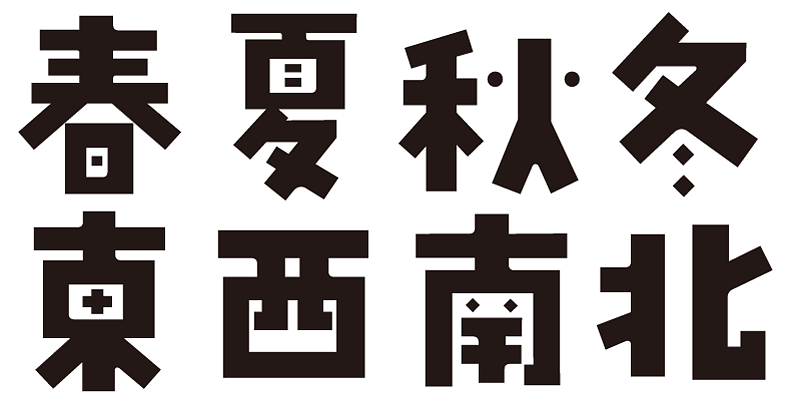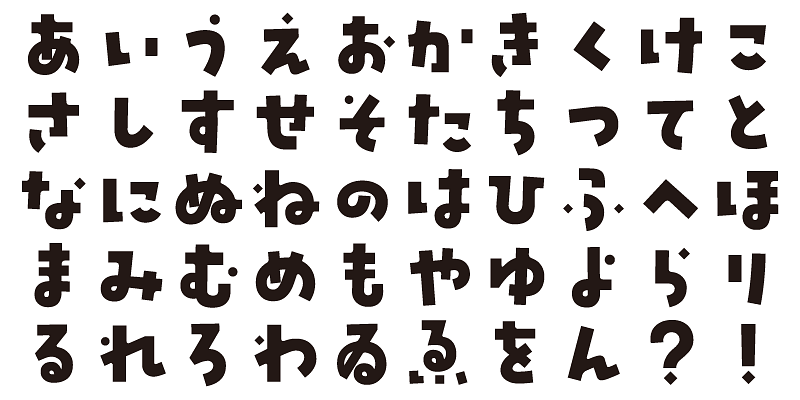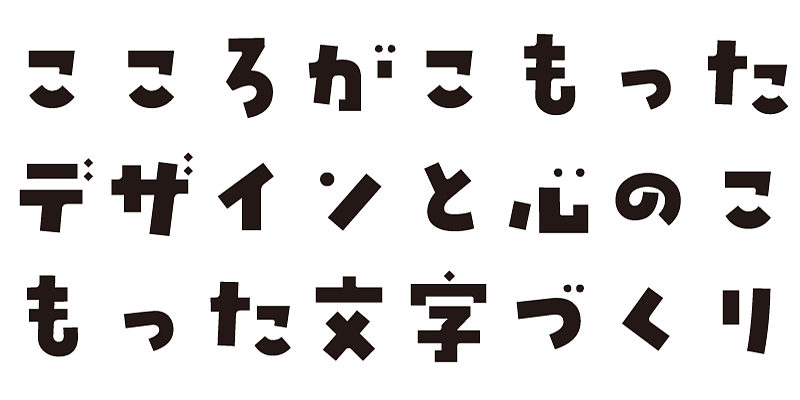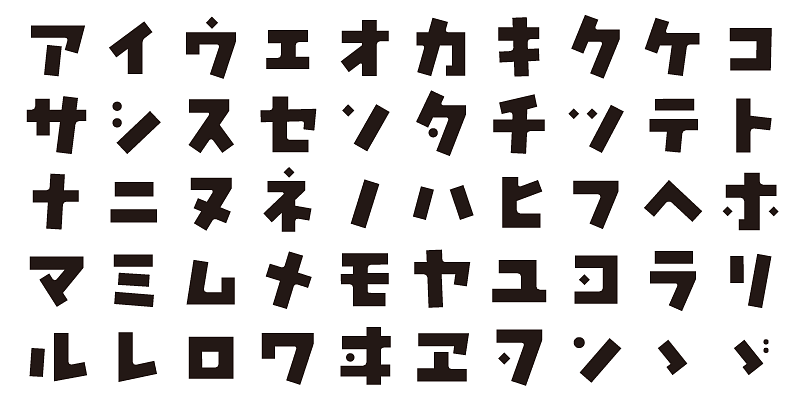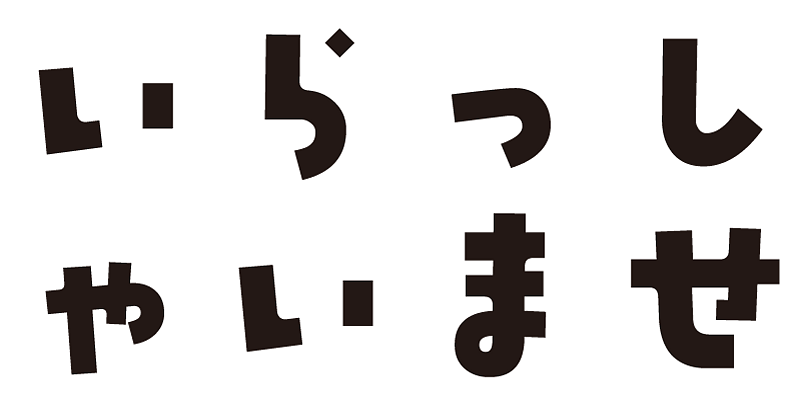
Diese Schrift strahlt Bewegung, Resonanz und Freude aus und hat eine verspielte Anmutung.
Neben 1.000 Kanji-Zeichen umfasst diese Schrift auch Hiragana-, Katakana-, alphanumerische sowie Interpunktionszeichen.
Wir entwerfen Schriften in der Hoffnung, dass sie den ausgedrückten Worten eine tiefere Bedeutung verleihen. Wir möchten, dass sich der Benutzer bei der Verwendung dieser Schriften wohlfühlt und Freude empfindet.